Tổng hợp 5 font Việt hóa nét tròn dễ thương
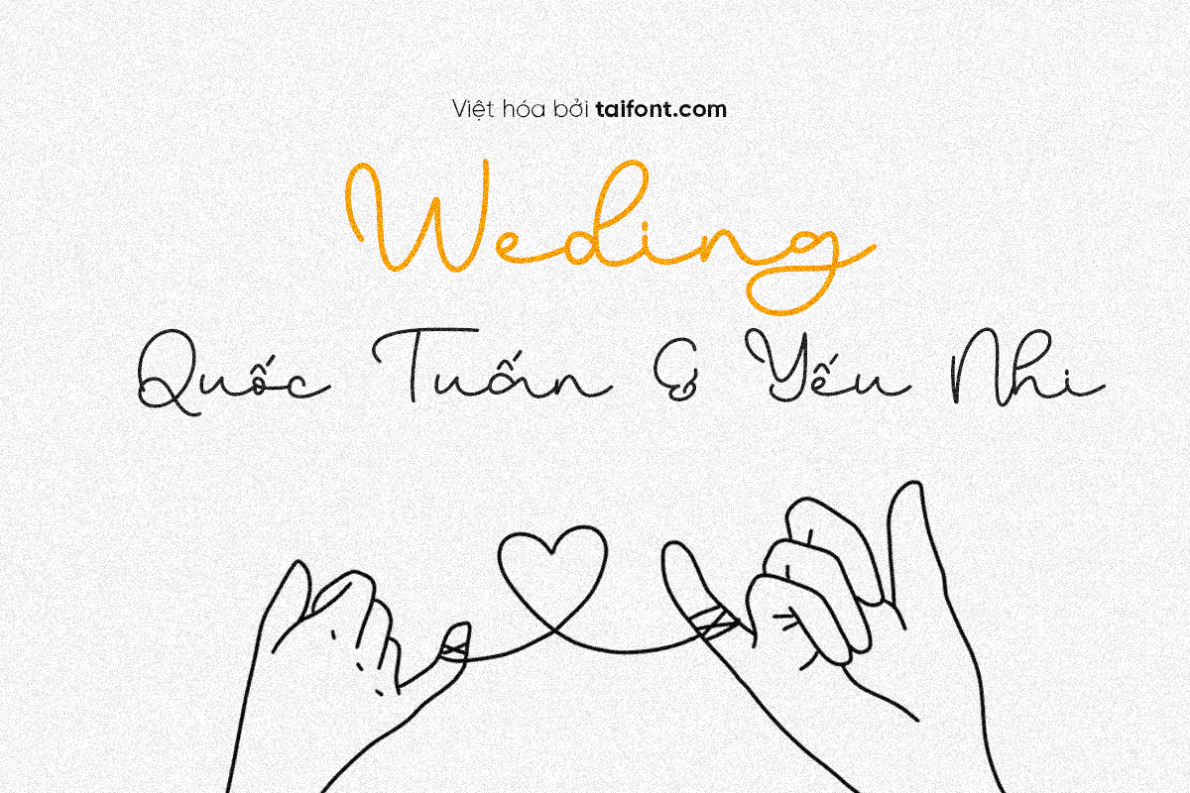
Tổng hợp 5 font Việt hóa nét tròn dễ thương, chủ yếu là font chữ ký việt hóa đẹp.
Font Việt hóa TF LittlePeace | Link tải
Font Việt hóa TF LittlePeace, một font chữ cực kỳ dễ thương với những nét tròn tuyệt vời.
Font Việt hóa TF Smooth Signature | Link tải
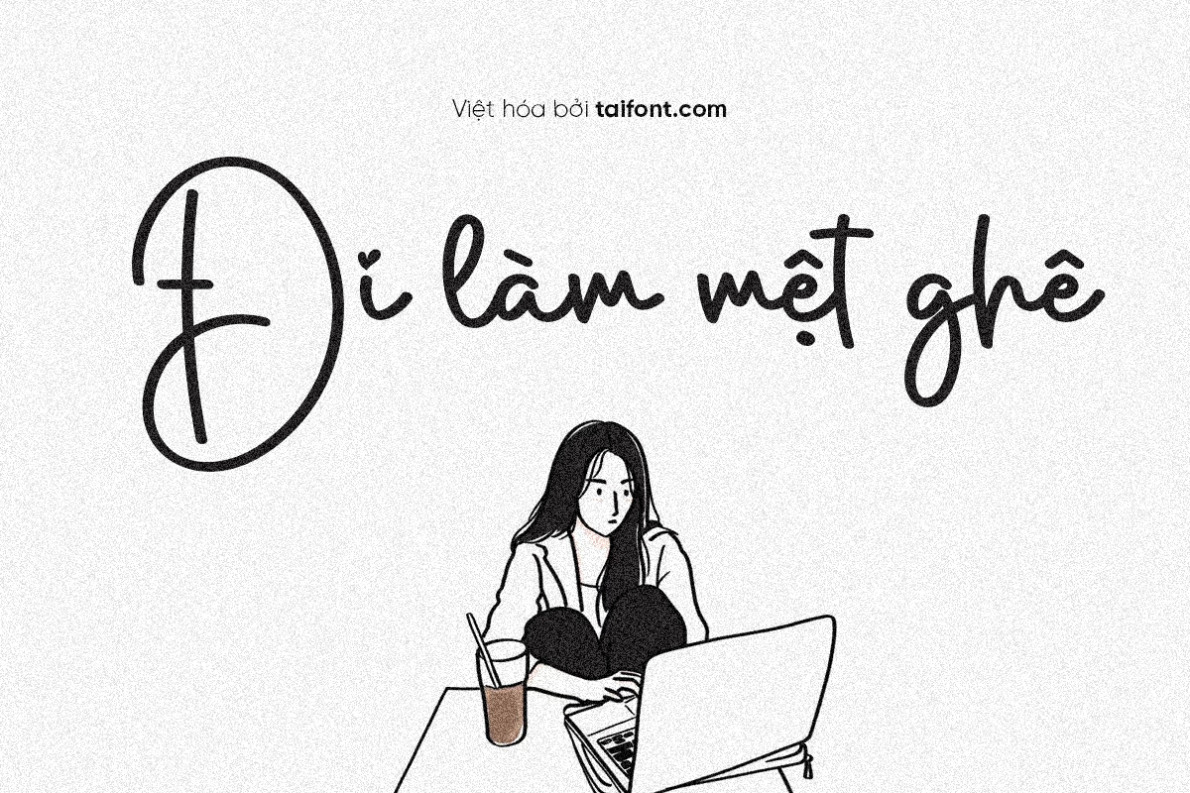
Font Việt hóa TF Smooth Signature là một font chữ tròn dày, nét đậm thật tuyệt đẹp.
Font Việt hóa TF Bingo Heyho | Link tải
Font Việt hóa TF Bingo Heyho quá tuyệt đẹp để thiết kế thiệp cưới nhé các bạn
Font Việt hóa TF Taylor | Link tải
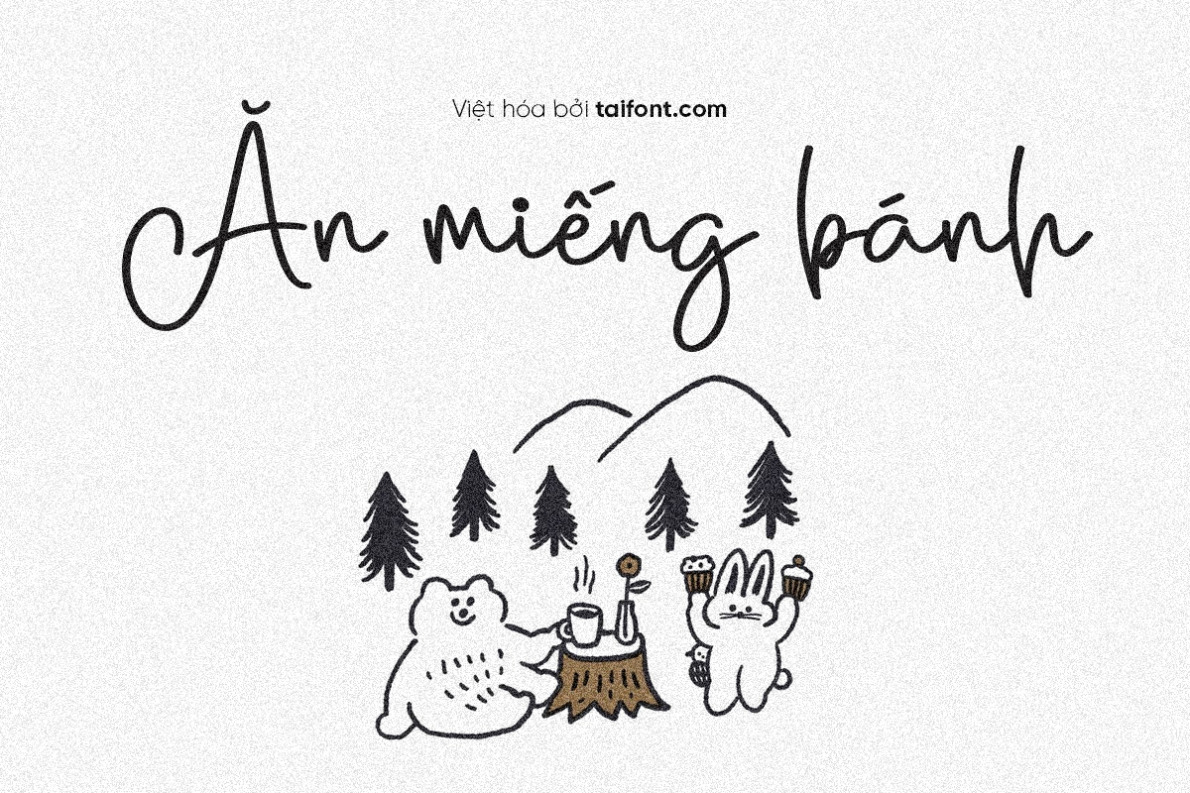
Font Việt hóa TF Taylor là một font Viết tay đẹp, tròn và dễ thương
Font Việt hóa TF Magic | Link tải
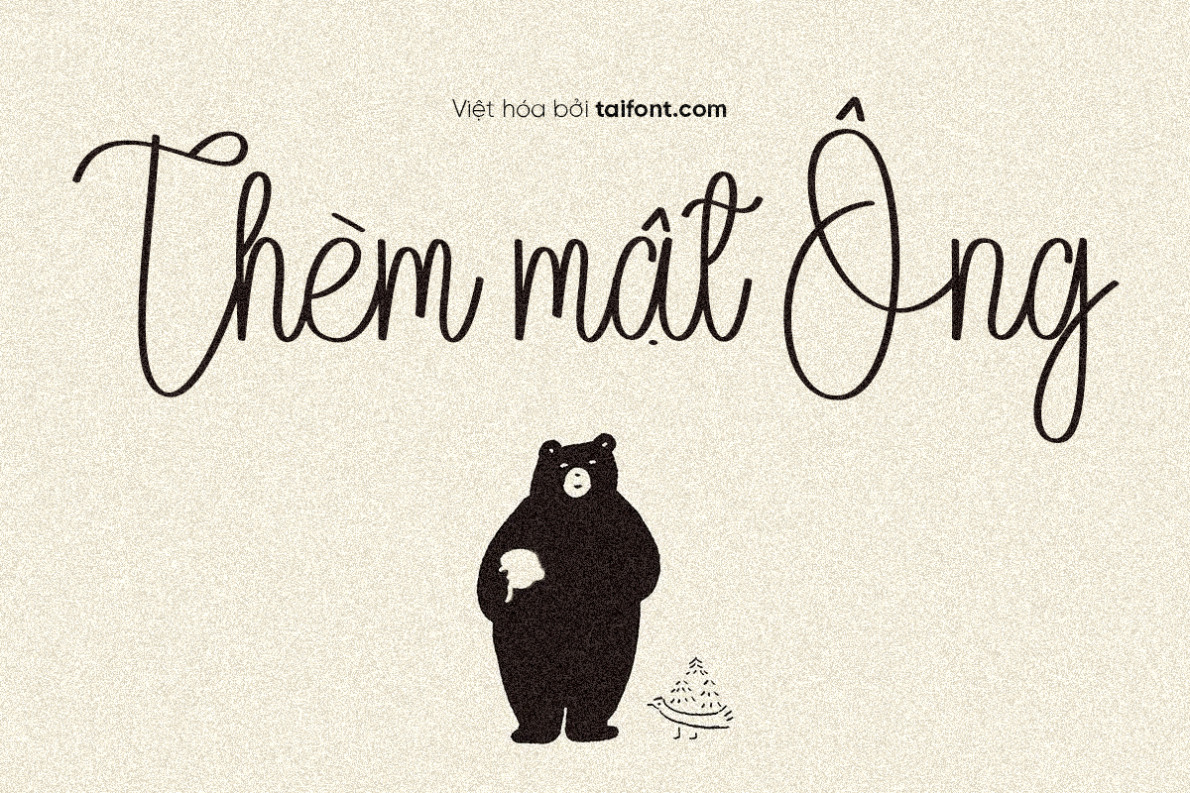
Font Việt hóa TF Magic là font viết tay có những nét dài cá tính.